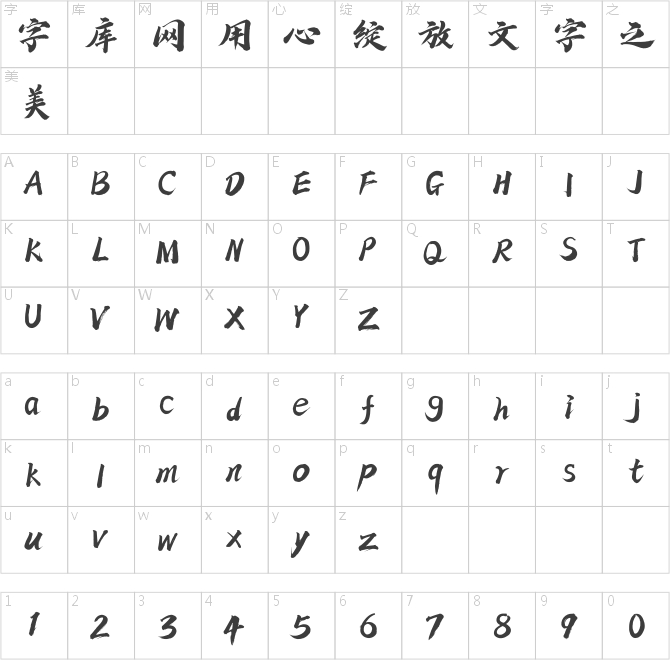
字体名称: 方正字迹-仝斌
方正字迹-仝斌飘逸体
方正字迹-仝斌飘逸体介绍
方正字迹-仝斌飘逸体,作者仝斌从事平面设计行业,多年的实战经验,让他对字体的结构,和笔画节奏有很深的理解。加之对生活的感悟和自身的书写习惯,字体在力与美之间寻找微妙的平衡,形成独特的刚柔并济的美感,个性鲜明,自成一体。适合于电影海报、包装、品牌名称、户外广告标题等。
方正字迹-仝斌飘逸体字体FZZJ-TBPYTJW字库是一款让人赏心悦目、百看不厌的中文字体,适合各类广告和产品包装设计应用,字体大小17.43MB,格式为TTF字体,上传用户是瓜皮,作者/版权方为方正字迹